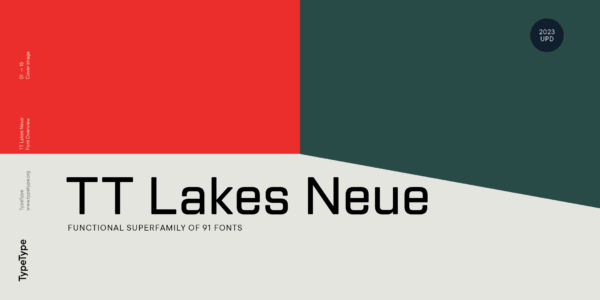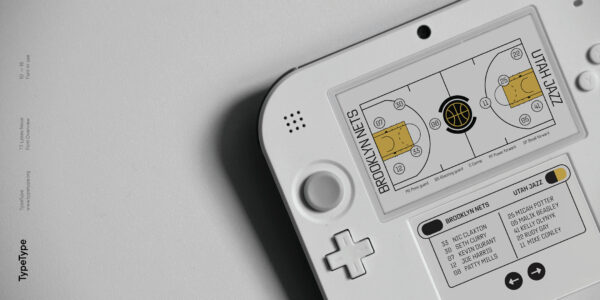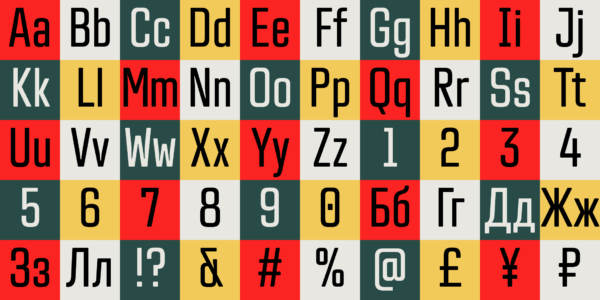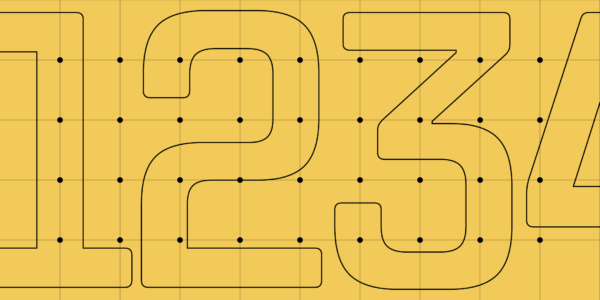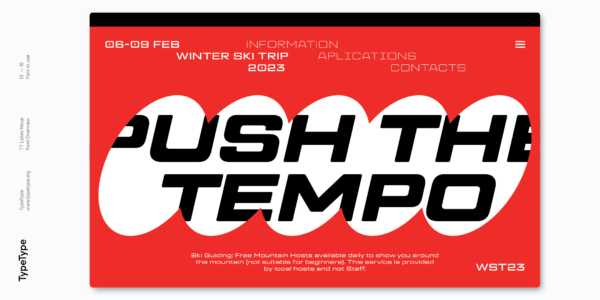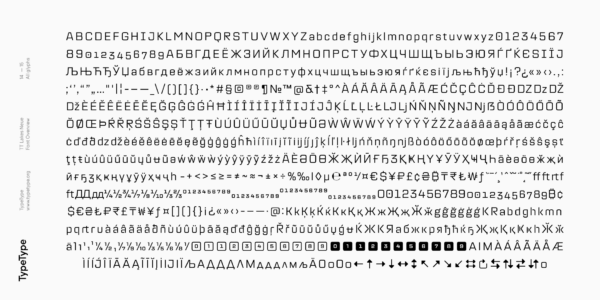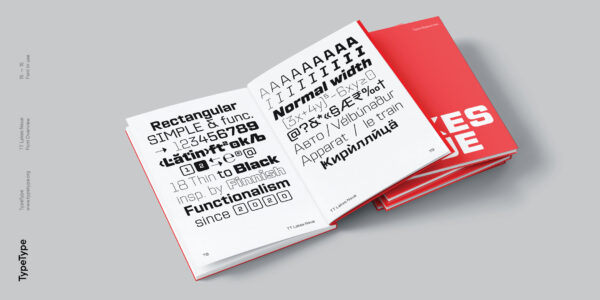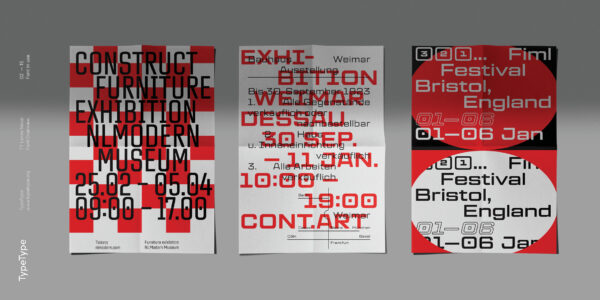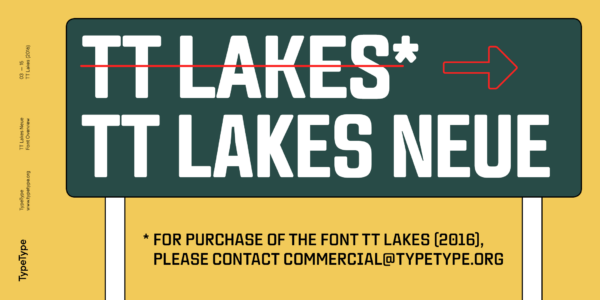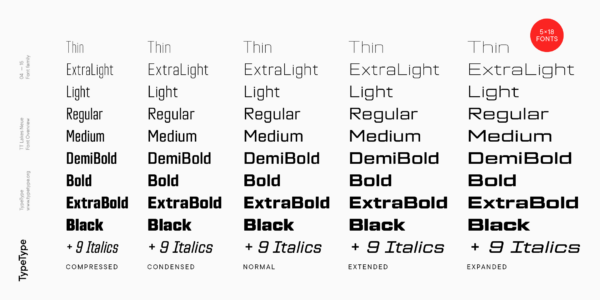
TT Lakes Neue
TT Lakes Neue — ТТ Лэйкс Нью
Произносится «ТТ Лэйкс Нью». «Lakes» — производное слово от lake, в переводе с английского «озеро», «Neue» — в переводе c немецкого «новый». Буквы «TT» являются аббревиатурой названия компании.
TT Lakes Neue — технологичный геометрический гротеск с финскими корнями. Вдохновением для его создания послужила надпись на табличке первой половины XX века.
TT Lakes Neue
Технологичный шрифт для игровой индустрии
TT Lakes Neue
TT Lakes Neue 2.0 — это очень современное шрифтовое семейство, предназначенное для интерфейсов игр различных жанров. В 2023 году мы серьезно обновили данный шрифт, успокоив визуально его внешний облик. TT Lakes Neue оставлялся по-прежнему узнаваемым, но при этом лишился акцидентных деталей. Формы знаков стали более спокойными и универсальными, что позволит его использовать в любом типе интерфейсов или проектов. Кроме визуальных правок некоторых знаков, мы проработали дополнительные стилистические сеты, которые могут придавать шрифту дополнительный стиль и характер.